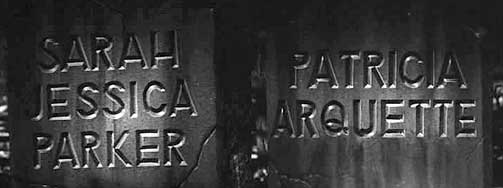
Schriften in folgenden Filmvorspännen
Hallo, ich suche die Schriften, die in folgenden Filmvorspännen verwendet werden. Die meisten habe ich schon herausbekommen.
1. Psycho (Hitchcock 1960), Vorspann von Saul Bass
Eine der American Gothics - aber der Apostroph passt nicht so ganz. Und in welchem breiten Schnitt ist "Psycho" gesetzt?
2. To Kill a Mockingbird (Mulligan 1962), Vorspann von Stephen Frankfurt
Akzidenz Grotesk Bold & Regular
3. Goldfinger (Hamilton 1964), Vorspann von Robert Brownjohn
Franklin Gothic Condensed
4. Ed Wood (Burton 1994), Vorspanngestalter unbekannt (?)
Keine Ahnung!
5. Dawn of the Dead (Zack Snyder 2004), Vorspann von Kyle Cooper
Impact... aber was ist "of the"?
Zu "Ed Wood":
Die Schrift auf den Grabsteinen ist in der Tat tricky, könnte fast individuell gefertigt sein - man vergleiche mal die 'R's von MURRAY mit den anderen.
Zu "Dawn of the Dead":
Schwierig, weil so wenige Buchstaben!? Eigentlich hätte ich gesagt eine der amerikanischen Gothics, aber das 'O' ist dafür zu eckig!
1. ALFRED HITCHCOCK’S >>> franklin gothic
PSYCHO >>> helvetica expanded
4. CHRIS LEBENZON
sehr ähnlich: compacta (nur das S hat keinen geraden mittelstrich ...)
5. OF THE >>> futura condensed light
4. CHRIS LEBENZON
sehr ähnlich: compacta (nur das S hat keinen geraden mittelstrich ...)
Der die abgerundete Rechteckform und gerade Strich/Fuß im R deutet auf eine Konstruktion auf Karopapier hin. Sehr ähnlich ist die Route 66 von Nicks Fonts.
Auf einigen Straßenschildern in Karlsruhe findet man eine entfernt ähnliche und vmtl. bis sicher handgezeichnete Grotesk. Und noch mal das gleiches Prinzip, aber andere Parameter: http://uwes.suche-plus.de/galerie5f.html. Daher könnte die Schrift auch eine Einzelanfertigung sein. :?
Zu "Ed Wood":
Die Schrift auf den Grabsteinen ist in der Tat tricky, könnte fast individuell gefertigt sein - man vergleiche mal die 'R's von MURRAY mit den anderen.
Ich glaube, es war früher generell sehr verbreitet, die Filmtitel mit der Hand zu schreiben – is mir schon sehr oft aufgefallen.
Ich habe noch mehr bzw. bessere Samples zu ED WOOD aufgetrieben. (Klicken für größeres Bild!)
Compacta und Route66 sind schon ziemlich nah dran!
Ich denke auch dass hier vieles handgezeichnet ist.
1. ALFRED HITCHCOCK’S >>> franklin gothic
Und da hat sich der Vorspanngestalter Saul Bass dann einfach einen Apostroph aus einer anderen Schrift geschnappt? Oder hatte eine alte Version der Franklin Gothic (noch) diesen Apostroph?
Ich glaube, es war früher generell sehr verbreitet, die Filmtitel mit der Hand zu schreiben – is mir schon sehr oft aufgefallen.
Gehe ich recht in der Annahme, das wir wohl keine genaueren Bezeichnungen für die Schriften in ED WOOD finden?
Wie würdet ihr die Schriften dann ganz allgemein beschreiben? Dass die Schriften den amerikanischen 1950ern nachempfunden sind, ist offensichtlich. Aber was gibt es über deren Charakter zu sagen? Welchen Zweck sollten die Schriften der damaligen Zeit erfüllen?
Gehe ich recht in der Annahme, das wir wohl keine genaueren Bezeichnungen für die Schriften in ED WOOD finden?
Wie würdet ihr die Schriften dann ganz allgemein beschreiben? Dass die Schriften den amerikanischen 1950ern nachempfunden sind, ist offensichtlich. Aber was gibt es über deren Charakter zu sagen? Welchen Zweck sollten die Schriften der damaligen Zeit erfüllen?
Die Grotesk ist IMHO eindeutig! Das ist eine „Grabsteinschrift”. Ähnliche Schriften wie die Bank Gothic und die Teuton (Storm Type Fonts) berufen sich auf Vorlagen von Grabsteinen aus dem späten 19ten bis frühen 20ten Jahrhundert.
Zur Bank Gothic findest Du in den 100 besten Schriften einen kurzen Hinweise dazu:
Morris Fuller Benton diente ein Grabstein aus dem späten 19. Jahrhundert als Anregung, dessen Inschrift er auf einer Frottage festhielt. Er schuf mit Bank Gothic eine reine Kapitälchenschrift, was sie noch technischer wirken lässt.
Ja, das war im alten Info-PDF für die Teuton. Dieses PDF habe ich seit ewigen Zeiten auf der Kiste. In der neuen PDF ist das Bild leider nicht mehr drinnen. :?
Allerdings steht dieser Hinweis noch im Text vom PDF:
und ganz unten auf der Teutonseite:
The present type face project “Teuton” parodies the above-mentioned hypothesis; it is immediately inspired by an inscription on one German tomb in the Sudetenland.
Bei der Schrift handelt es sich also um eine „Grabsteingrotesk”. :(